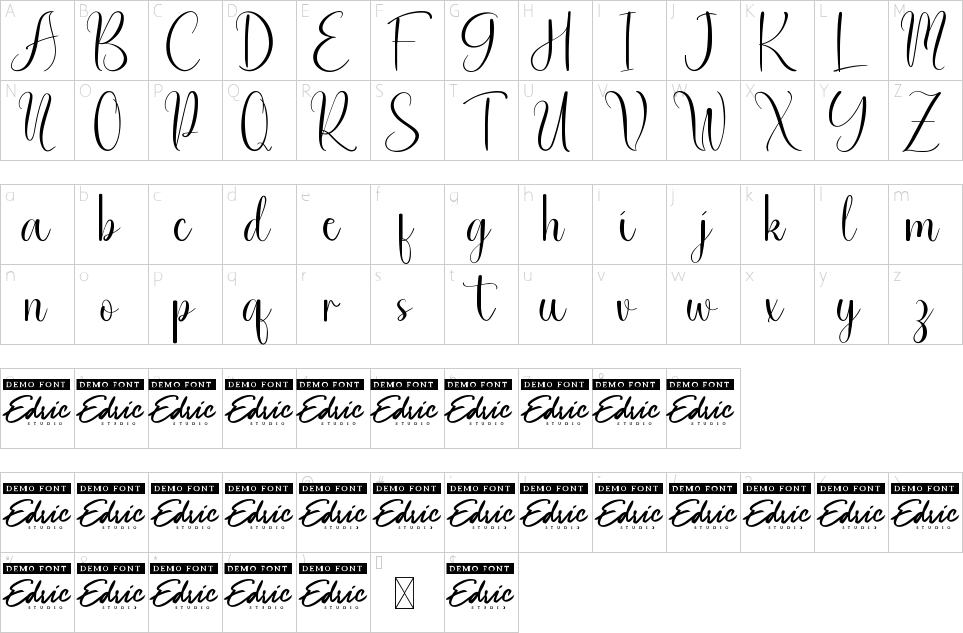
A fonte Good Nature é uma opção elegante e agradável para quem busca uma fonte minimalista e elegante para projetos pessoais ou profissionais. Ela foi projetada pelo designer desconhecido edricstudio e é uma escolha perfeita para um ambiente gráfico natural e suave. Com seu design simples e limpo, Good Nature se destaca como uma fonte acessível para aqueles que estão em busca de uma fonte de texto de alta qualidade, sem comprometer a estética. Recentemente, Good Nature foi baixada mais de 874 vezes, o que provavelmente reflete o seu valor e agradável uso. Esta fonte é uma ótima escolha para projetos que valorizam tanto a funcionalidade quanto a beleza. É perfeita para criações que buscam uma atmosfera natural e acolhedora, sem perder a elegância e a praticidade que a Good Nature oferece.